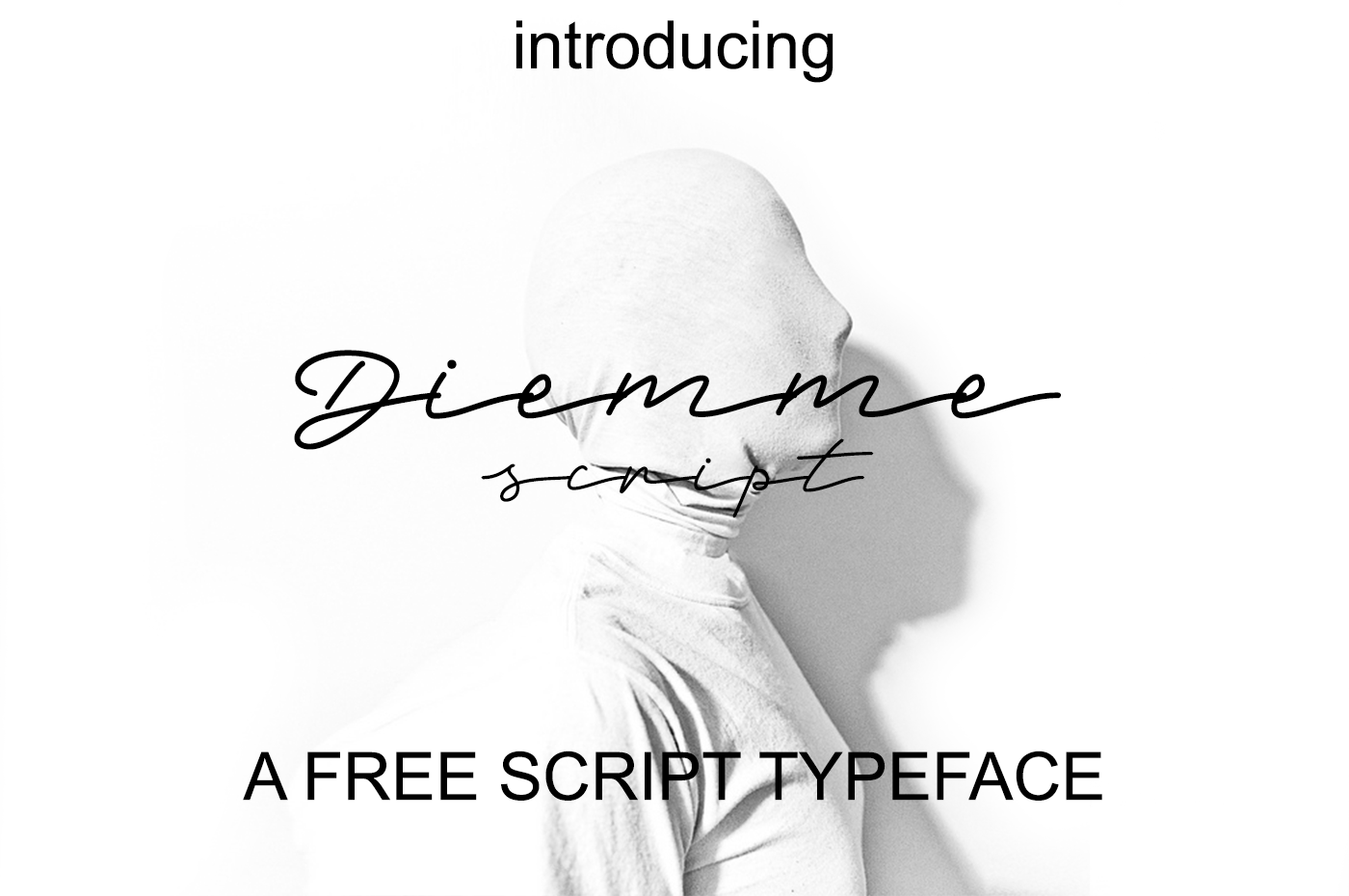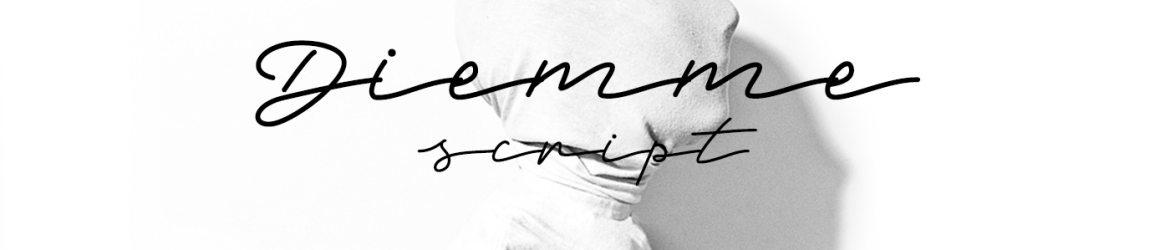
Diemme Script Font – Download Grátis
Descubra Diemme Script Font, uma elegante nova opção para designers digitais. Introduzida pelo designer de tipo Polythene Designs, essa fonte script é perfeita tanto para aplicações modernas quanto para os mais tradicionais projetos. Seja criando um logotipo de produto inovador, um cartão de casamento com toques vintage ou uma marca de roupas elegante e sofisticada, Diemme Script trará profissionalismo e personalidade ao seu design. Suave e limpo, mas repleto de detalhes meticulosamente concebidos, essa fonte é a escolha ideal para aqueles que valorizam tanto o estilo quanto a funcionalidade em seus projetos de identidade visual. Não perca tempo – experimente Diemme Script Font hoje. Ele está aqui para tornar sua próxima criação ainda mais única e memorável.